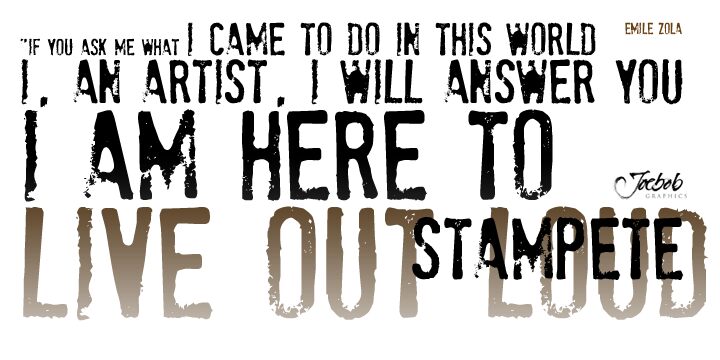
stamPete, creata da J O E B O B graphics, è un carattere gratuito "stamp style" in maiuscolo, che richiama l'effetto rude dell'inchiostro impresso su superfici vissute. Bordi irregolari, imperfezioni e l'usura tipica del timbro conferiscono alle lettere un carattere artigianale e industriale, lontano da ogni finitura digitale.
La texture usurata aggiunge una presenza fisica e graffiante a poster di concerti e copertine di dischi, donando un aspetto autenticamente vissuto a brand di streetwear, packaging di birrifici e insegne. Scegli questo font gratuito quando il design deve richiamare marchi da officina, grafica punk o il classico timbro di gomma.